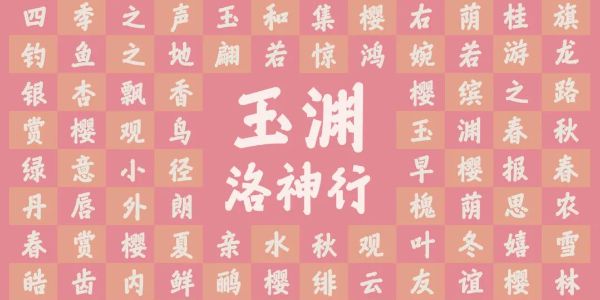
汉仪x玉渊潭联名字体 | 玉渊潭畔,墨舞樱姿
{{tag.name}}玉渊潭公园的樱花季,是北京春日里最令人期待的盛事之一。52年的樱花园历史,36年的樱花季传承,早已让这里成为无数人心中不可替代的春日记忆。每年樱花绽放的季节,玉渊潭公园便化身为一片粉色的海洋,吸引着八方来客,共同见证这场自然与人文交织的盛大节日。
从文人雅士隐居之所钓鱼台,到今日赏花踏春之地玉渊潭,玉渊潭公园见证了京城的历史变迁,连接着古今之人赏花吟诗之情。
汉仪股份近期与北京玉渊潭公园的深度合作,展现了其在字体设计领域的创新能力和全链路解决方案的实力。通过与玉渊潭公园的联名字体设计、樱花节导视系统升级,汉字文创产品开发以及“时光字迹”展览,汉仪不仅将字体设计与公园的文化特色深度融合,还通过多维度的应用场景,赋予汉字新的生命力,进一步推动了汉字文化的传播与创新。
汉仪玉渊洛神行,是汉仪字库与玉渊潭公园联合推出的公园主题字体。基于对玉渊潭文化底蕴的深刻感悟,灵感来自元代书法家赵孟頫的行书《洛神赋》卷,打造的一款独一无二的视觉符号。
汉仪玉渊洛神行,不仅是对传统书法美学的致敬,更是对玉渊潭文化底蕴的现代诠释。兼具文人雅士之古韵与现代简约之审美,具有优雅的书卷气息,展现了汉字书法在现代语境下的全新生命力。
从"玉渊洛神行"到汉字文化,以字体为起点,以汉字文化为核心,汉仪与玉渊潭共同策划“时光字迹·汉字书体的美学流变”主题展览,以时间为叙事脉络,从甲骨文的原始神秘到数字字体的跨界创新,追溯汉字三千年书体演变的史诗旅程。通过四大板块,展现汉字如何从祭祀符号升华为文化基因,从技术工具蜕变为艺术媒介。
游客漫步在落樱缤纷的樱花园中,不仅能感受自然之美带来的视觉震撼,还能在字里行间感受到汉字的演变之美,使春日游园升华为一次穿越时空邂逅汉字文化的沉浸体验。
汉仪与玉渊潭公园的合作,为我们展示了字体更多的潜力。汉仪玉渊洛神行,突破字体工具属性,打破纸面与屏幕的维度限制,从“二维”到“多维”广泛应用于公园的导视系统、导览地图、文创产品、主题展览、活动宣传等各个方面,用统一的汉字视觉形象贯穿始末,提升公园的品牌辨识度。这种“字体+”的模式,打通了从数字资产到实体产品的转化通道,连接文化与体验,为游客创造更深层次的游园记忆。
今年,园区内的哈根达斯冰激凌汽车,车身皮肤也将字体元素巧妙地融合整体设计中。更值得一提的是,汉仪与玉渊潭公园携手推出以字体为核心创作元素的限定文创周边,突破了以往单一的樱花视觉,将汉字文化与公园的美丽景观相结合,如樱花磁扣泡泡本、玉渊洛神行文字钥匙扣、玉渊洛神行文字冰箱贴拼图等创意产品,已在公园文创商店上架,可满足不同游客的消费需求。“有颜、有料、有趣、有用”,形成了独特的文化表达。
玉渊潭公园园区的视觉焕新,正以“润物细无声”的方式影响着游客的游园体验,重塑城市公共空间的文化价值。不仅如此,园区中举办的"时光字迹·汉字书体的美学流变"主题展览,以"汉仪玉渊洛神行"为视觉锚点,通过纱幕互动、字体装置等形式,让游客在感受玉渊潭文化底蕴的同时也能更深入的了解汉字文化。
汉仪与北京玉渊潭公园的合作,以字体为媒介,通过深入融合公园的特色与历史底蕴,打造了一套完整的文化产业链条。这一系列文化项目不仅突破了字体设计的传统边界,更以多元化的形式为游客创造了沉浸式的游园体验,为字体设计的未来发展提供了新的方向。这种跨界融合的模式,展现了字体设计在文化赋能与商业价值挖掘中的无限可能。